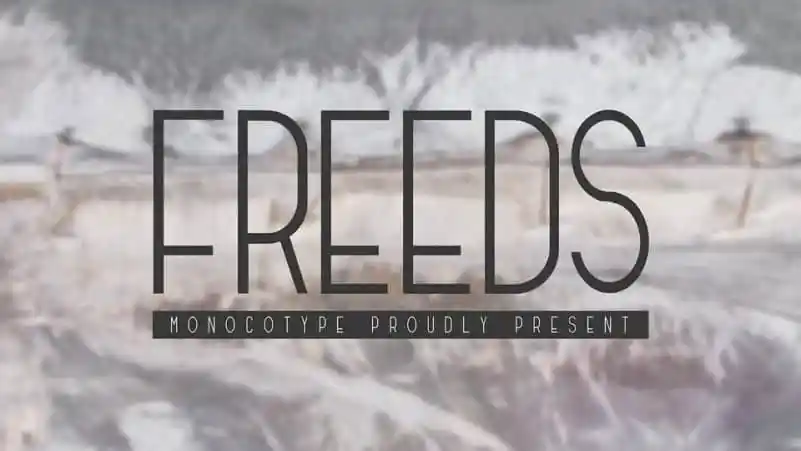
Freeds Sans Serif Font – Download Grátis
A Freeds Sans Serif Font é uma elegante tipografia moderna que se destaca por sua versatilidade e estilo único. Perfeitamente adaptada para uma ampla gama de aplicações, especialmente para títulos e linhas curtas de texto em ambientes impressos e digitais. Esta fonte foi criada pelo designer Refialdi Dwi Putranto através do site 99designs. Com linhas limpas e bordas afiadas, a Freeds é um tipo livre que inclui letras maiúsculas, números e símbolos. Uma fonte extremamente versátil, ela se torna perfeita para identidades de marca, casamentos, convites, frases ou anúncios. A Freeds está disponível tanto em formato digital quanto impresso, adaptando-se ao estilo moderno que você pode incorporar nos projetos mais diversos como logotipos, revistas e até mesmo publicações digitais. Com uma estrutura simples e limpa, a Freeds oferece um design sofisticado e contemporâneo. Seja para um evento especial ou apenas um material de marketing, esta fonte torna-se uma escolha ótima que reflete sua personalidade única em cada palavra impressa. Uma vez que o uso desta fonte é gratuito, você pode abusar disso com sua criatividade e estilizar qualquer projeto digital ou impresso.